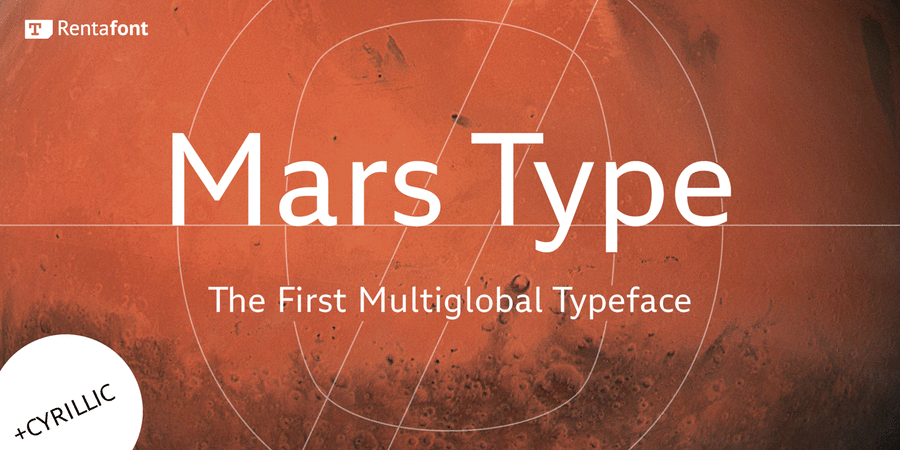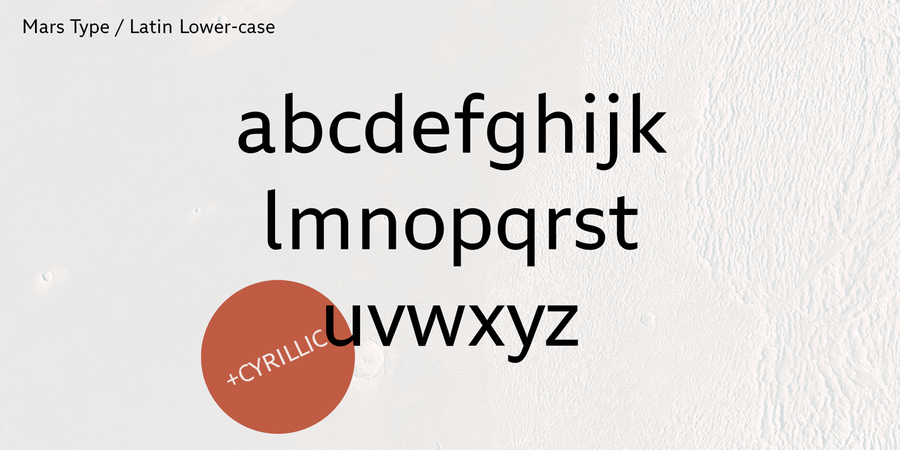
Mars Type – це гротеск з відкритими формами та іншими рисами, що підвищують його розрізнюваність і читабельність. Ідеально підходить для навігації та інтерфейсів у марсіанській колонії. Головною фішкою шрифту є особлива форма овалів (ідеальне коло зовні, «ілюмінатор» всередині) та відповідність кута нахилу деяких знаків (слеш) куту нахилу осі обертання Марсу – 25,19°. Вертикальні зрізи відкритих знаків, як у шрифтах Futura та Gill Sans, дозволяють новому шрифту бути містким, як гуманістичні гротески, зберігаючи геометричність. Шрифт Mars Type розроблено Євгеном Садко у 2018-2019 році та випущено компанією Rentafont під безкоштовною ліцензією SIL Open Font License (OFL).
Асоціації з сімейством шрифтів Mars TypeОсобистість і характер гарнітури:
міський, сучасний, лаконічний, точний, формальний, ясний, рівний, зрозумілий, якісний, Простий, серйозний, спокійний, чіткий, різкий, твердий, глобалізований, розумний, глобалістічний, інженерний, креслярський, космічний, переконливий, практичний, прагматичний, технічний, урбаністичний, логічний, гладенький, комфортний, зручний, непомітний